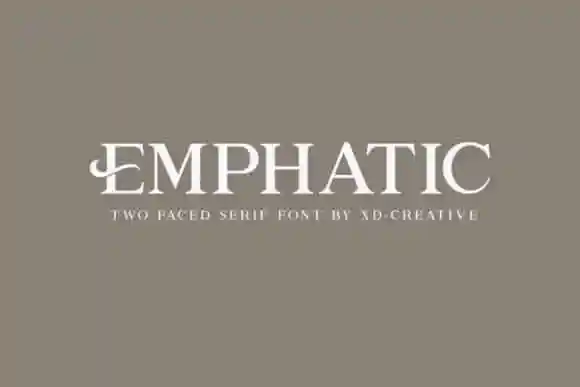
Emphatic Serif Font – Fonte Grátis
Emphatic Serif Font
Introduzimos a Emphatic Serif Font, uma tipografia serif com um ar contemporâneo e clássico. Esta fonte foi projetada para ter uma aparência única e está feita com diversas alternativas de fontes. Kudocreative é o criador desta font elegante e autêntica, simples e elegantemente concebida. Ela se adapta facilmente a um amplo conjunto de projetos, tornando-a perfeita para complementar suas ideias criativas. Sinta-se à vontade para adicionar esta fonte às suas criações e veja como ela as faz brilhar.